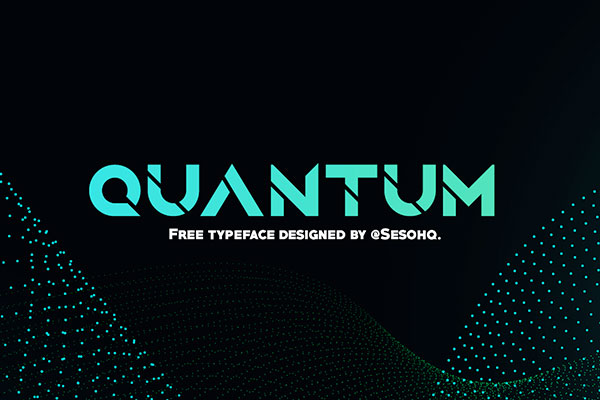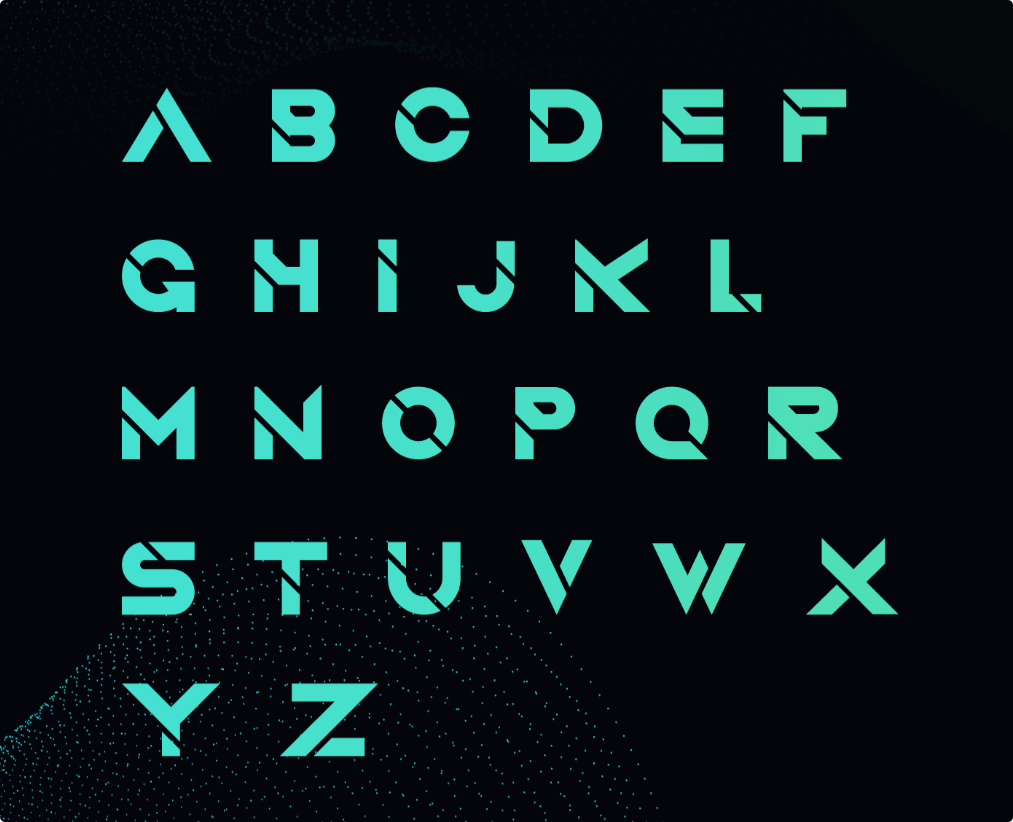
QUANTUM字体
QUANTUM是由Ortiz创建的一款充满创新的大胆字体。这款独特字体的设计灵感来源于形状生成器工具和大胆的口音元素。通过在字母的原始笔画上进行精炼的削减和前卫的未来派设计,QUANTUM呈现出与众不同的风格,非常适合与游戏、空间、未来、科幻等概念相关的各种应用场景。同时,它也是徽标、品牌和标题设计的理想选择。
QUANTUM字体效果预览